今回は、自然のやさしさや瑞々しさを感じさせる「植物」をモチーフにした日本語フリーフォントをご紹介します。
葉っぱの形や草花の揺らぎを感じるようなフォルム、自然からインスピレーションを受けた柔らかな曲線など植物的なデザインをまとったフォントは、見た人の心にそっと寄り添うあたたかさを感じる素敵なフォントばかりです。
今回は、かわいらしい草花の印象をまとったフォントから、上品な和の雰囲気を漂わせるものまで、ピックアップしましたのでぜひ参考ください。
「植物をモチーフ」のおすすめフォントまとめ
以下のサンプル画像は本記事で紹介している一部ですが、文字に植物のモチーフを取り入れた可愛らしいそんなフォントデザインをまとめてみました。
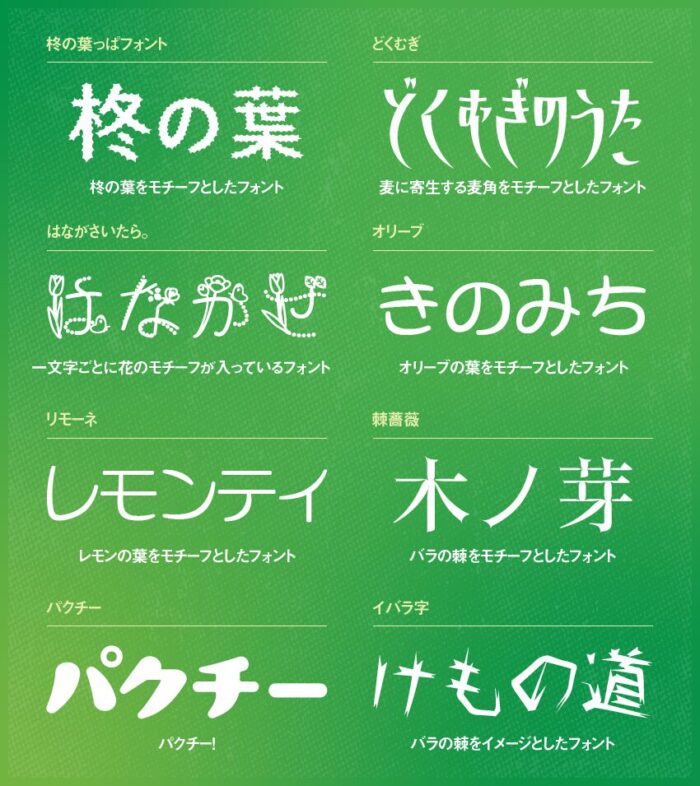
柊の葉っぱフォント
柊の葉っぱフォントは、「柊の葉」をイメージして作られたトゲトゲしたフォルムが特徴的なデザインフォントです。
はながさいたら
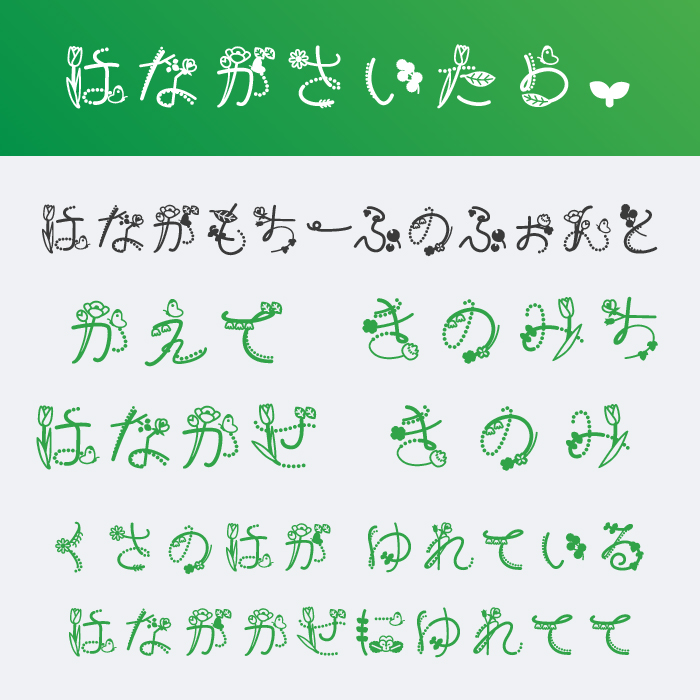
はながさいたら。フォントは、一文字ごとに花のモチーフが入っているユニークで可愛らしいひらがなフォントです。花のデザインも複数のパターンがあるも可愛いです。
どくむぎ
どくむぎフォントは、麦に寄生する麦角をモチーフにしており、毒々しさと素朴さの表現されているデザインフォントになります。鋭角の鋭さが、毒々しさもあるユニークなフォントです。
パクチー
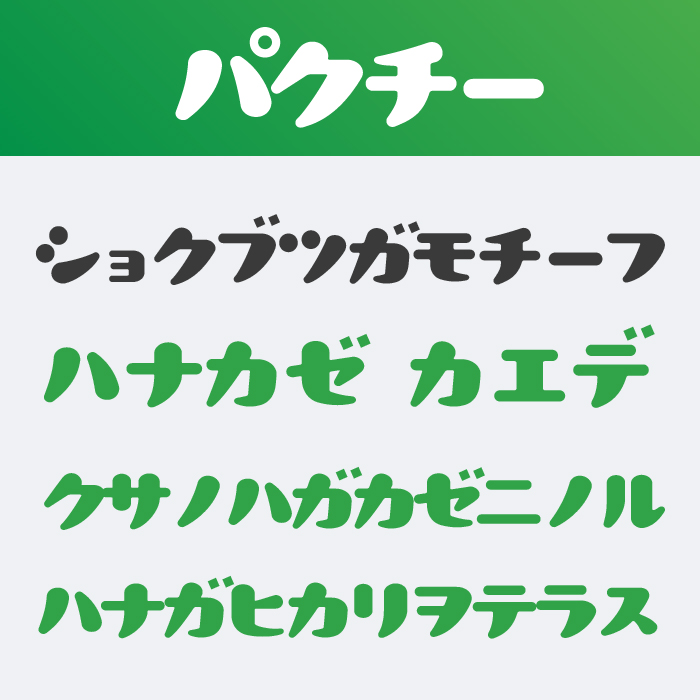
パクチーフォントは、ぷくっとした膨らみがとっても印象的なフォントです。レトロな雰囲気を持ち合わせているので、ロゴやキャッチコピーなどとの相性がとっても良さそうです。
リモーネ
AFSリモーネフォントは、丸ゴシック体をベースにレモンの葉をイメージした「はらい」がデザインが特徴的なフォントです。
オリーブ
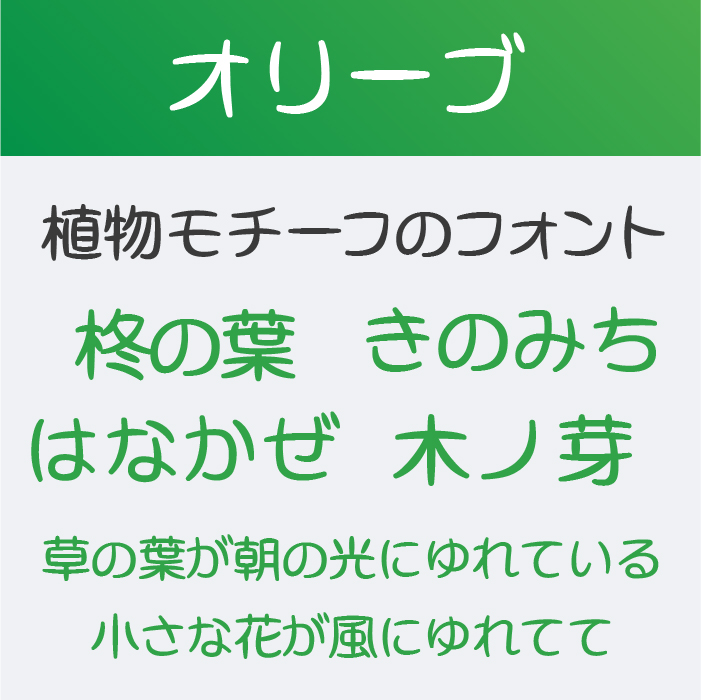
AFSオリーブフォントは、オリーブの葉っぱをモチーフとして制作されたデザインフォントです。葉っぱのように、線の頭と尾の部分が先細ったようなフォルムになっているので、少し変わった印象のデザインとなっています。
棘薔薇
棘薔薇フォントは、文字先が薔薇の棘のようになっているデザインが特徴的なフォントです。
イバラ字
イバラ字フォントは、文字の先端がトゲトゲしており植物の「いばら」をイメージされたいる文字デザインです。
黒薔薇シンデレラ
黒薔薇シンデレラ&赤薔薇シンデレラフォントは、長体ゴシック体をベースに薔薇のようにトゲトゲの装飾されているユニークなデザインフォントです。